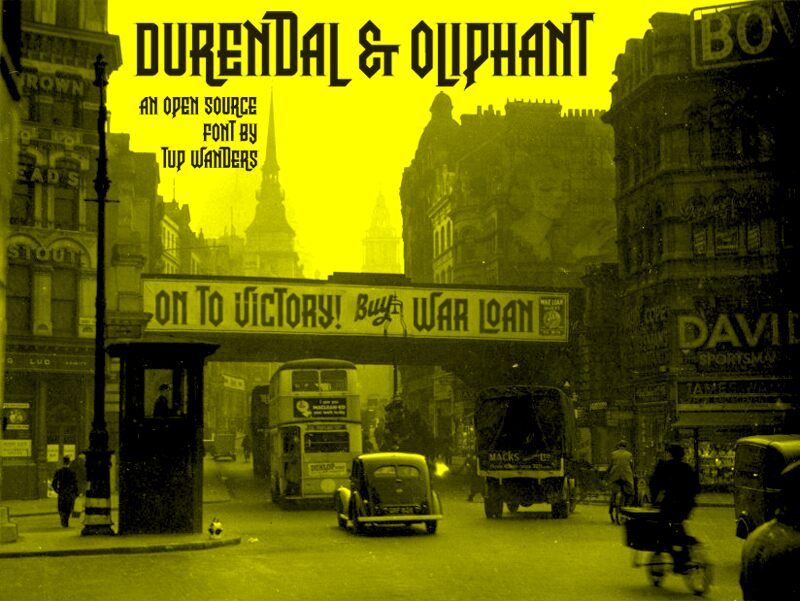
Durendal & Oliphant von Tup Wanders ist eine moderne, kostenlose Gothic-Versalschrift mit einer harten, heraldischen Ausstrahlung. Die Buchstaben verbinden die Dramatik der Blackletter mit hohen, blockartigen Silhouetten. Dank scharfer Diagonalen und prägnanter Übergänge entsteht ein spannungsgeladener Rhythmus, der zugleich mittelalterlich und modern wirkt.
Sie eignet sich perfekt für Branding im Bereich Dark Fashion, Metal- und Fantasy-Poster, Spieletitel, Buchcover und Eventgrafiken – überall dort, wo kurze Zeilen Gewicht und eine feierliche Note benötigen. Als kostenlose Schrift ist sie ideal für Monogramme, Logowörter und Überschriften, da die Versalien wie Banner ineinandergreifen, statt nur ruhig auf der Seite zu stehen.
Die Schrift enthält zahlreiche Ligaturen und Variationen und unterstützt viele Sprachen.
Enthält nur Großbuchstaben.